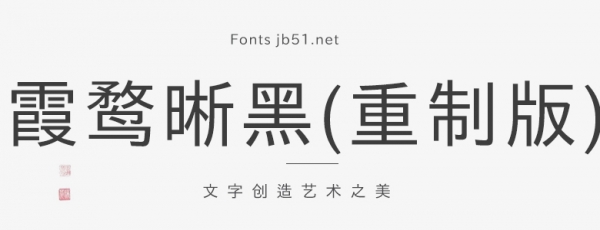
本項(xiàng)目“霞鶩晰黑”爲(wèi)“IPAex ゴシック”的衍生字型項(xiàng)目,在原始字型的基礎(chǔ)上,利用原有的部件和筆形,增補(bǔ)原始字型未包含的字,并對(duì)原有的部分漢字按照舊式印刷常見字形進(jìn)行調(diào)整。此外,簡化了一些部件的出腳(如“枸”“間”“陶”“崗”等字中“口”“日”“缶”“山”部件的出腳),使字形更加簡約。
2020 年末,本項(xiàng)目創(chuàng)建,以一點(diǎn)字坊“傳承字形標(biāo)準(zhǔn)化文件”爲(wèi)主要參考,對(duì)“IPAex ゴシック”進(jìn)行改造(詳見 legacy 分支)。后由于傳承字形部件規(guī)則的複雜性,以及時(shí)間原因,本項(xiàng)目曾于 2021 年 7 月放棄維護(hù)并歸檔。由于近來“霞鶩新晰黑”和“霞鶩新緻宋”的發(fā)佈和持續(xù)完善,2024 年春,本人決定重啓該項(xiàng)目,并創(chuàng)建新項(xiàng)目“霞鶩緻宋”,在“霞鶩新晰黑/新緻宋”基礎(chǔ)上回歸舊字形寫法,原有“霞鶩晰黑”推倒重來。
總體計(jì)劃
本字型計(jì)劃發(fā)佈兩種不同字形版本。
Classic(CL)版: 參考早期鉛字印刷字形常見寫法,回歸舊式印刷字形,合併一部分“源規(guī)格分離”原則下分化的異碼字。
Modern(MN)版: 採用兼顧當(dāng)代慣用筆形的折中印刷字形(非楷化字形),嚴(yán)格遵循“源規(guī)格分離”原則。